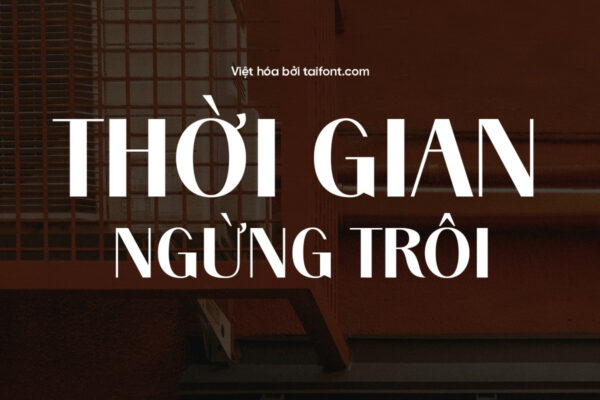
Giới thiệu Font TF Devroon Royale Việt hóa: Tinh Hoa Sang Trọng
Bạn tìm kiếm một font có chân (serif) toát lên vẻ quý phái, tinh tế và sở hữu kho glyphs (ký tự đặc biệt) lộng lẫy? TF Devroon Royale Việt hóa chính là lựa chọn đỉnh cao, mang đến sự hoàn hảo và đẳng cấp cho các thiết kế cao cấp.
Đặc Điểm & Ứng Dụng Độc Quyền
TF Devroon Royale Việt hóa nổi bật với các nét chân duyên dáng, tỷ lệ thanh lịch cùng sự phong phú của các ký tự thay thế nghệ thuật (swashes, alternates).
• Thời trang & Tạp chí: Đây là font lý tưởng cho các thương hiệu xa xỉ. Hoàn hảo cho trang bìa tạp chí, tiêu đề bài viết, logo thời trang, hoặc nhãn mác sản phẩm mỹ phẩm cao cấp. Các glyphs đẹp mắt giúp tên thương hiệu trở nên độc đáo và tinh xảo.
• Thiệp Mời & Ấn phẩm Cao cấp: Font này mang lại cảm giác vương giả và trang trọng cho thiệp cưới, thư mời VIP, hoặc các ấn phẩm kỷ niệm.
• Branding: Sử dụng Devroon Royale để xây dựng hình ảnh thương hiệu tinh tế, chuyên nghiệp và đẳng cấp quốc tế.
Devroon Royale Việt hóa giúp thiết kế của bạn trở thành một tác phẩm nghệ thuật hoàn hảo, cuốn hút và mang đậm phong thái thượng lưu.